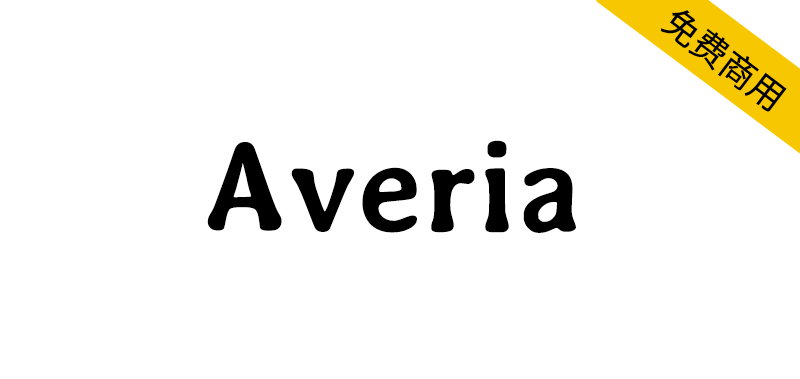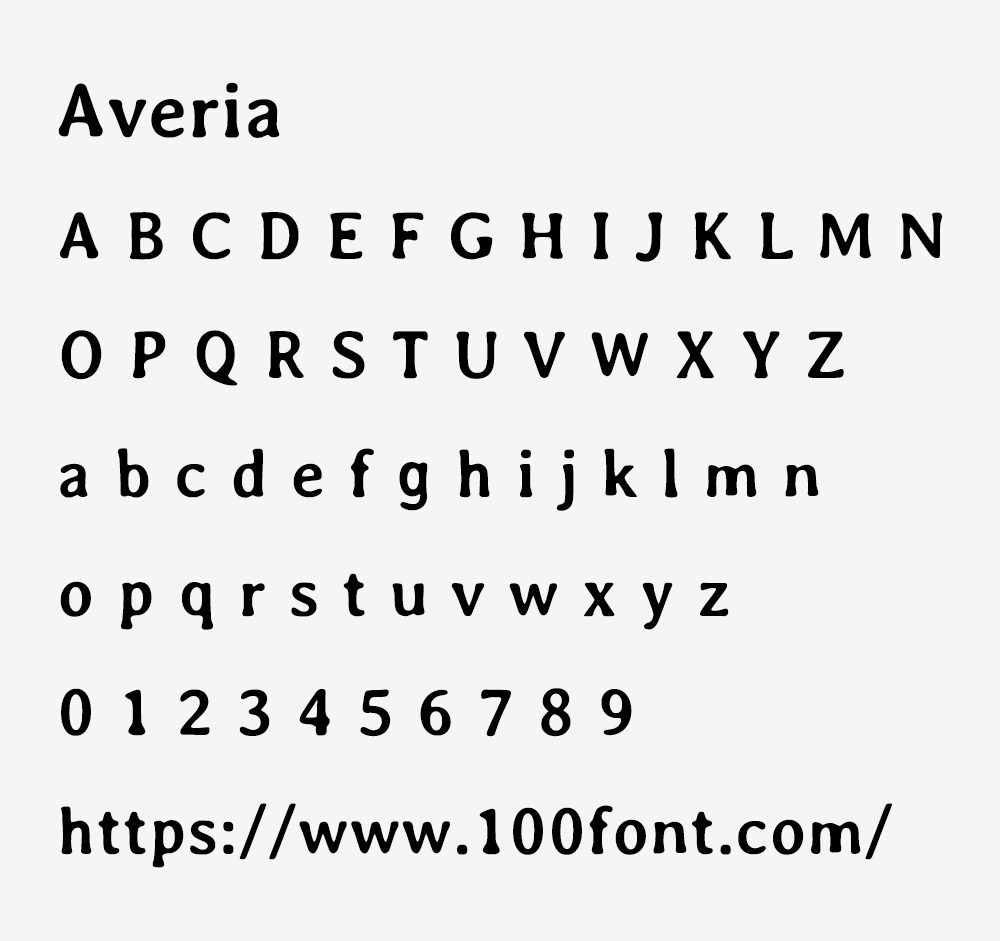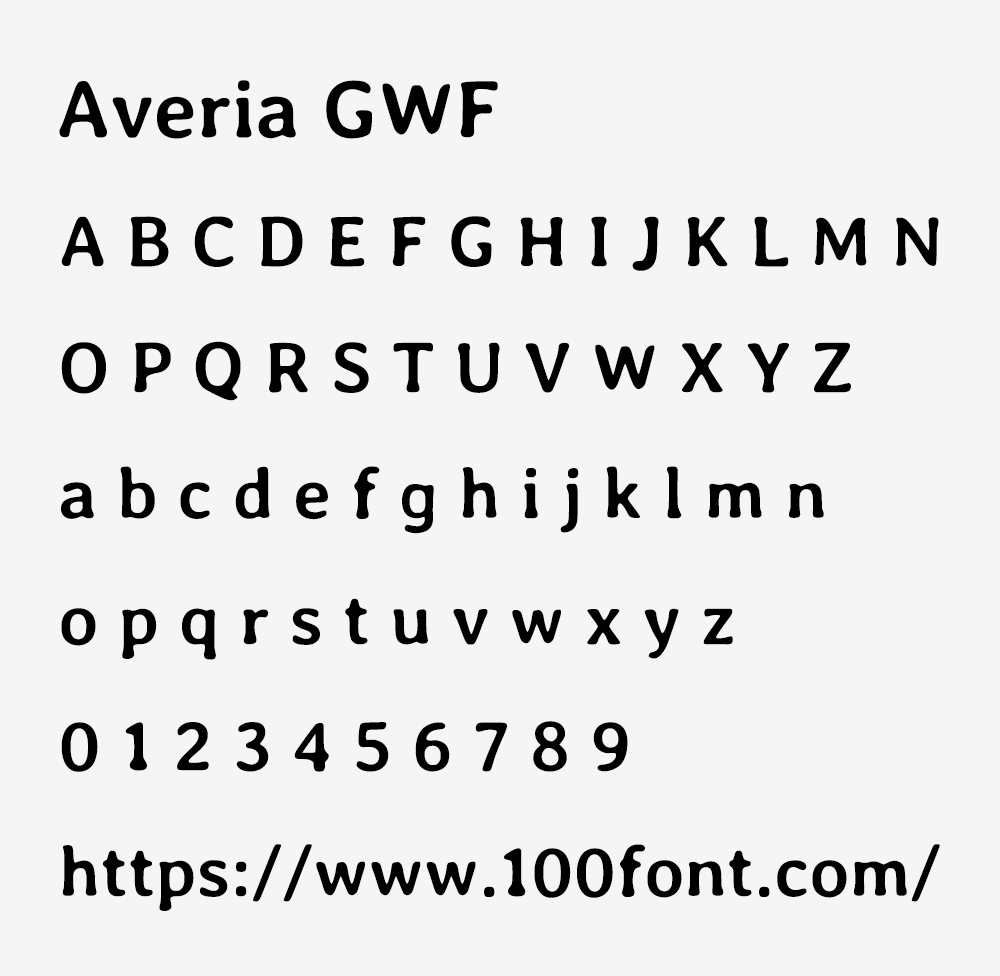
Averia是一套免费开源的字体家族,由Dan Sayers设计,灵感来源于古老的印刷体和手写风格,同时融入了现代数字字体的可读性。它的设计特点是带有轻微的“磨损”或“不完美”效果,模拟传统印刷或墨水浸染的质感,给人一种复古、有机的感觉。适合复古风格的设计、书籍排版、海报、品牌标识等,由于可读性良好,也可用于正文阅读。如果你喜欢带有手工艺感的字体,Averia 会是一个很有个性的选择!
Averia GWF:是 Averia 字体家族的一个变体,专为网页优化设计,它保留了 Averia 系列标志性的“复古印刷”风格,同时针对屏幕显示进行了细节调整,减少像素模糊或锯齿问题,确保在网页上具有良好的可读性和渲染效果。